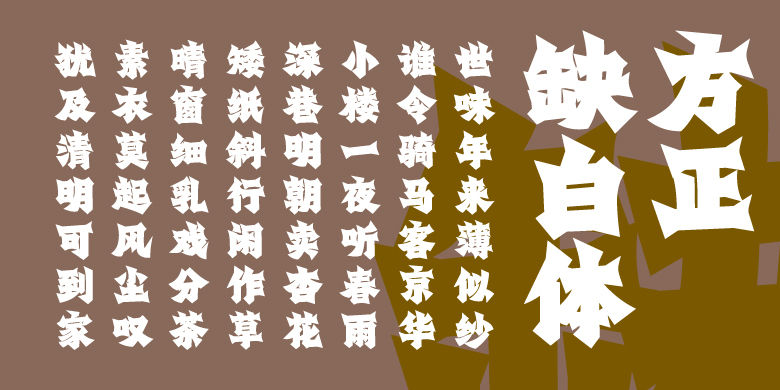
方正缺白体
侯嘉祺
创意字体
缺即是美,是中国人对生命的一种退让。月有阴晴圆缺,花有开放凋零,本就是人生常态。若固守完美,势必缘木求鱼。这款《缺白》的灵感便来源于此,作者借鉴了魏碑风格,在极为“满”的字面率中寻找“缺”,即字体的“内白”(即负空间),刻意将字体的“缺”压缩到极小,但它们又真实存在,但又希望这套字体“满”而藏“缺”。这是汉字设计中黑与白的游戏,作者极力地在字体中探寻中国古典美学的价值观。